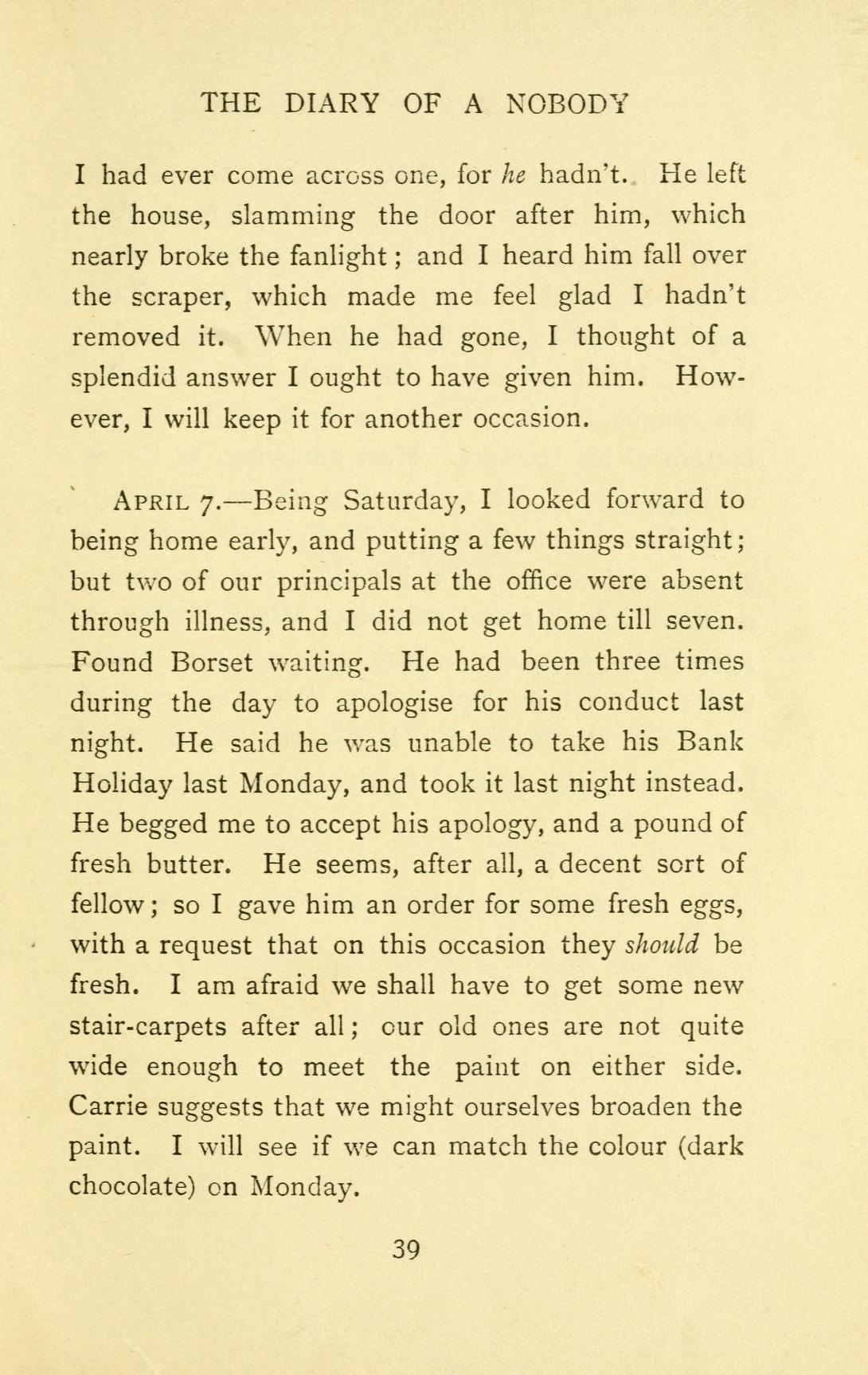
Typische amerikanische Buchschrift
Diese Schrift findet sich in vielen ( älteren) amerikanischen Büchern. Welche könnte das sein?
Quelle: "Diary of a Nobody", 1906
Meinst du die im englischen Sprachraum gebräuchliche Klassifizierung der Serif-Schriften in Old Style, Transitional, Modern und Egyptian?
Die Old Style-Gruppe ist gekennzeichnet durch a low contrast in stroke weight and angled serifs (wie Garamond).
Die Transitional-Schriften haben a more vertical axis and sharper serifs (wie Baskerville).
Also ... ich kann mich da nicht richtig entscheiden, das historische Schriftbeispiel (immerhin von 1906) scheint irgendwie dazwischen zu sein.
Deshalb spreche ich auch nur von Ähnlichkeit.
Baskerville? Aber nur so was wie die Old Face, Old Style ... Es konnte auch etwas wie die Century Old Style von  Morris Fuller Benton (1909) sein? Oder irgendwas von Monotype um 1900 rum?  Auch sehr ähnlich wäre die Caslon Old Face. Hier findest Du auf Identifont eine Auswahl von Schriften von William Caslon (1693-1766):
Die William Caslon Text sieht sehr gut aus.
Von der gehe ich weiter. Identifont liefert da einiges an ähnlichen Schriften. Gleich die erste Alternative sitzt schon sehr nahe dran.
Monotype Old Style (1901) Zitat: "A renovation of Caslon Old Face."
Und damit sind wir genau da, wo Liuscorne auch schon (aber über Baskerville?)  angekommen ist ...
Gibt es Baskervilles ohne das kleine "g" mit Schlaufe?
Ich dachte eher an die "Old Styles" Ende 19., Anfang 20. Jahrhundert. Hier z.B. die Monotype-Variante von 1901:
Ganz grob würde ich folgendes vermuten: Es handelt sich um eine Old Style aus der Zeit um 1900, basierend auf der Caslon Old Face. Die Monotype Old Style ist nahe dran ... aber auch keine perfekte Lösung ...